Polices de Monotype
Le Studio Monotype est un groupe collaboratif et passionné de designers renommés du monde entier. Des classiques intemporels qui apportent une familiarité réconfortante aux futuristes polices qui forment les mots sur nos écrans, une grande partie du travail du Studio Monotype est constituée des caractères qui décorent notre vie de tous les jours.
Nouveau venu du studio Monotype, Cotford est un empattement contemporain créé par le directeur de la création typographique, Tom Foley.Dynamique, adaptable et surprenant, Cotford est un empattement langoureux qui va des minces délicats, se pliant et s'étirant comme des tiges de fleurs, aux poids lourds audacieux qui dominent la page et l'écran avec assurance et un charme vintage. En tant que Variable police, Cotford permet aux concepteurs d'explorer et d'affiner le design presque à l'infini, en découvrant ses nombreuses tonalités visuelles et ses secrets cachés.
Conçu par Malou Verlomme du studio Monotype, Macklin est une superfamille qui rassemble plusieurs styles qui attirent l'attention. Macklin est une police de caractères élégante et très contrastée, qui exige une attention particulière. Elle a été conçue à dessein pour permettre aux marques d'attirer les consommateurs modernes de manière plus émotionnelle. Macklin comprend quatre sous-familles -Sans, Slab, Text et Display- ainsi qu'une variable. La superfamille complète comprend 54 polices avec 9 graisses allant du hairline au noir.
La famille de caractères Tazugane Gothic est le premier caractère japonais original de Monotype. Conçue par Akira Kobayashi, Kazuhiro Yamada et Ryota Doi du studio Monotype, la police de caractères Tazugane Gothic propose dix graisses et a été développée pour compléter la police de caractères latine classiqueNeue Frutiger. La conception de la police de caractères Tazugane Gothic équilibre un style original et humaniste avec des éléments de l'écriture japonaise traditionnelle. Les deux polices de caractères fonctionnent ensemble de manière naturelle, transparente et adaptable, de sorte que les textes japonais et latins peuvent être utilisés côte à côte. Cela permet un large éventail d'applications, notamment dans les magazines, les livres et autres médias imprimés, sur les appareils numériques, dans les systèmes de marque et d'identité d'entreprise, et dans la signalisation des bâtiments, des autoroutes et des transports en commun.
Helvetica Now 2.0 s'appuie sur le travail révolutionnaire de la version 2019 de Helvetica Now - toute la clarté, la simplicité et la neutralité de l'Helvetica classique avec tout ce dont les concepteurs du 21e siècle ont besoin. Dans cette version 2021, nous introduisons l'Helvetica Now Variable et ajoutons des graisses condensées à l'Helvetica Now statique polices. Helvetica Now 2.0 comprend 96 polices dans trois tailles optiques distinctes (Micro, Text, et Display), avec maintenant 48 nouvelles graisses condensées. L'Helvetica Now Variable polices en comprend encore plus : 144 instances-48 normales, 48 condensées et 48 compressées.
FS Renaissance est un caractère d'affichage au pochoir créé par le studio Monotype. Fruit d'une collaboration entre l'artiste typographe et designer Craig Back et le directeur de la création typographique Pedro Arilla, le style unique police explore l'intersection entre l'art et le design. L'artiste et le designer travaillant main dans la main, chaque lettre a été conçue comme une œuvre d'art autonome, tout en fonctionnant harmonieusement ensemble comme une police de caractères fonctionnelle.
Vary par Olli Meier est un caractère géométrique sans empattement inspiré du cyrillique bulgare. Le Vary est amusant et adaptable et a été construit avec trois sentiments (variations) : classique, moderne, et loopy, offrant une opportunité aux designers d'être ludiques dans leurs créations. L'inspiration du cyrillique bulgare se retrouve principalement dans le caractère "g", qui s'inspire d'un " ?" manuscrit peu commun repéré par le créateur dans une vitrine de Sofia, en Bulgarie. Lorsqu'il a retourné ce dessin à 180°, le caractère latin "g" est né pour Vary. Un autre exemple est le "R" dans le set stylistique moderne, qui a été inspiré par le caractère cyrillique manuscrit " ?".
Depuis près de 90 ans, le Futura de Paul Renner est aussi populaire que polyvalent, des livres pour enfants aux magazines de mode en passant par la plaque sur la Lune. Futura est une icône typographique.Futura Now offre aux designers la possibilité de voir Futura d'un œil nouveau. Il est plus proche de Futura que n'importe quelle version numérique avec laquelle vous avez déjà travaillé. "Il redonne au monde des caractères géométriques sans empattement l'humanité dont il a tant besoin", déclare Steve Matteson, directeur de la création typographique chez Monotype, qui a dirigé l'équipe de conception.
Ambiguity est une famille de caractères composée de cinq personnalités ou "états" distincts, créée pour inciter les designers et les marques à sortir de leur zone de confort. Elle englobe à la fois la tradition et la radicalité, ainsi que la générosité et l'économie, nous encourageant à remettre en question nos croyances sur l'intersection du style et de la signification. La famille est conçue par Charles Nix, qui décrit Ambiguity comme "une expérience de pensée autant qu'une police de caractères". Ses cinq états - Tradition, Radical, Économe, Généreux et Normal - expriment ou subvertissent chacun des aspects différents de la tradition typographique.
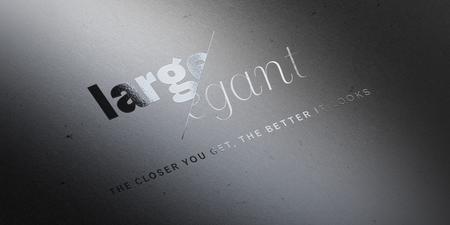
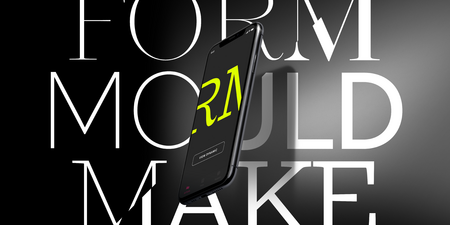
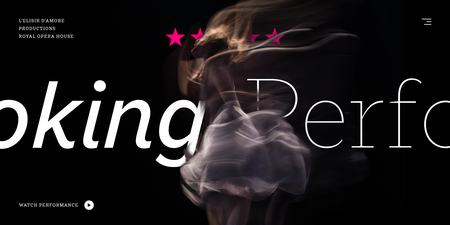
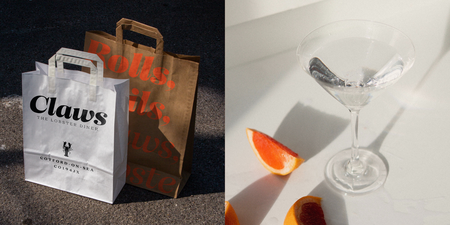
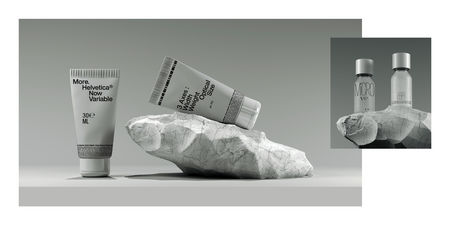
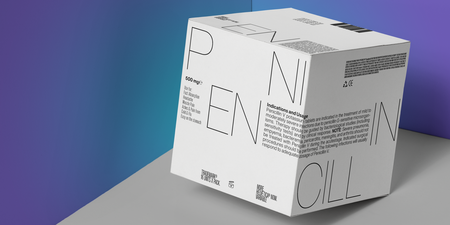
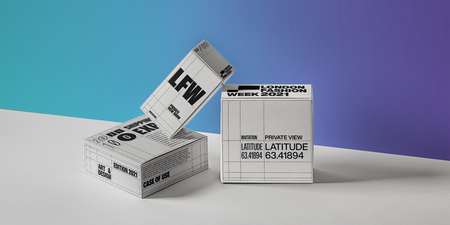
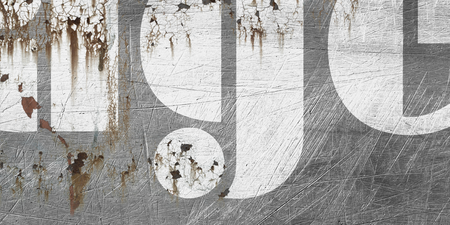
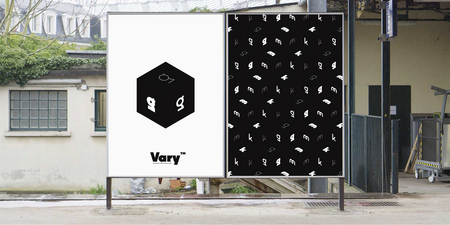
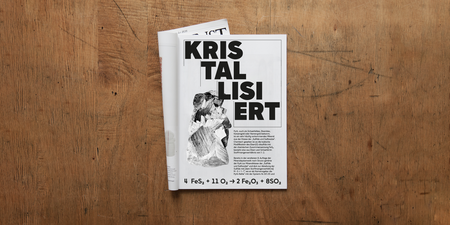
Polices de Monotype.
Le studio Monotype allie technologie et expertise pour créer des caractères remarquables. Animé par la passion de la typographie et par une attitude "tout est permis", le studio Monotype est au cœur de la plus grande bibliothèque de polices de l'histoire du monde.
Directeur créatif de type
Tom Foley
Tom Foley est directeur de la création typographique chez Monotype et, à ce titre, il est responsable de la direction d'une équipe de dessinateurs de caractères qui créent polices pour la bibliothèque de Monotype et les marques d'entreprise. Tom a les mots et les lettres dans le sang - son arrière-grand-père était issu d'une famille de tailleurs de pierre spécialisés dans la sculpture de lettres, et son oncle était peintre d'enseignes.
Directeur créatif de type
Vaishnavi Murthy Yerkadithaya
Basée à Bangalore, en Inde, Vaishnavi est une créatrice de caractères qui s'intéresse de près au monde des langues écrites. Inspirée par les connaissances de son grand-père en matière d'écritures anciennes, elle a transformé sa fascination d'enfant en carrière en poursuivant une maîtrise en conception de caractères à l'université de Reading, grâce à une bourse Felix.